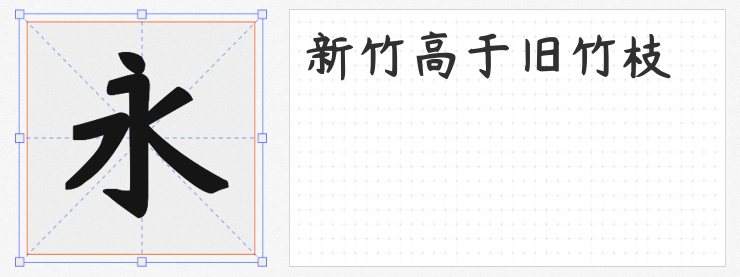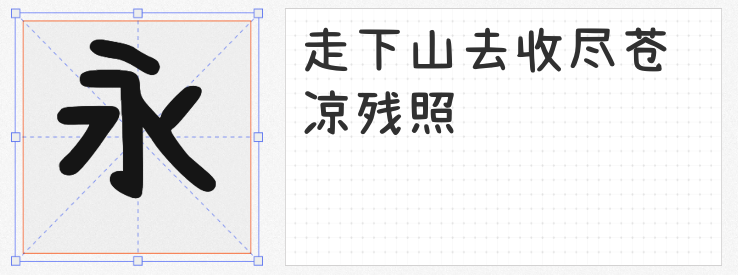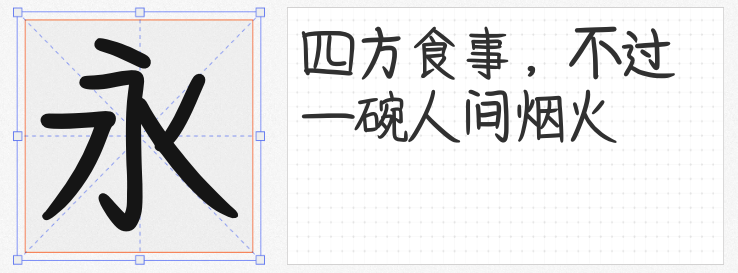
在平面设计与视觉传达领域,手写字体以其独特的温度感和个性化魅力,成为打破刻板印象、传递情感的重要工具。本文精选四款可免费商用的优质手写字体,涵盖不同风格与适用场景,助力设计师轻松提升作品质感。
由设计师杨任东创作的竹石体,以“竹”为灵感,将挺拔的线条与自然的书写韵律结合。其Bold版本字形简洁大气,笔画粗细过渡自然,既保留手写体的灵动感,又具备印刷体的清晰度。支持中英文及数字符号,适配艺术设计、书籍印刷、网页标题等场景,尤其适合需要传递文化底蕴或现代简约风格的项目。
这款字体通过字重变化呈现双重风格:轻字重时笔画粗细对比鲜明,交接处自然粘连,还原水笔书写时的真实笔触;重字重时则线条圆润饱满,整体更显可爱俏皮。无论是品牌包装、海报标题还是社交媒体配图,濑户2.0都能通过动态的字重调整,为设计注入活泼气息。
由国内设计师lxfly2000在B站FontForge教学视频中免费分享的Acy手写体,以粗体形式呈现,笔画粗壮有力却不失手写痕迹。其略带倾斜的字母设计,为英文排版增添动感,适合作为标题或重点信息突出展示。作为开源字体,它不仅支持商用,更体现了设计社区的共享精神。
云峰字库出品的云峰林桥体,以极致工整的笔画结构诠释手写字体的另一种可能。每一笔都严谨规范,却因自然的起笔收笔保留了书写温度。这款字体适合需要强调专业性与规范性的场景,如教育类海报、企业报告或传统工艺品牌设计,传递稳重而不失亲和力的视觉语言。